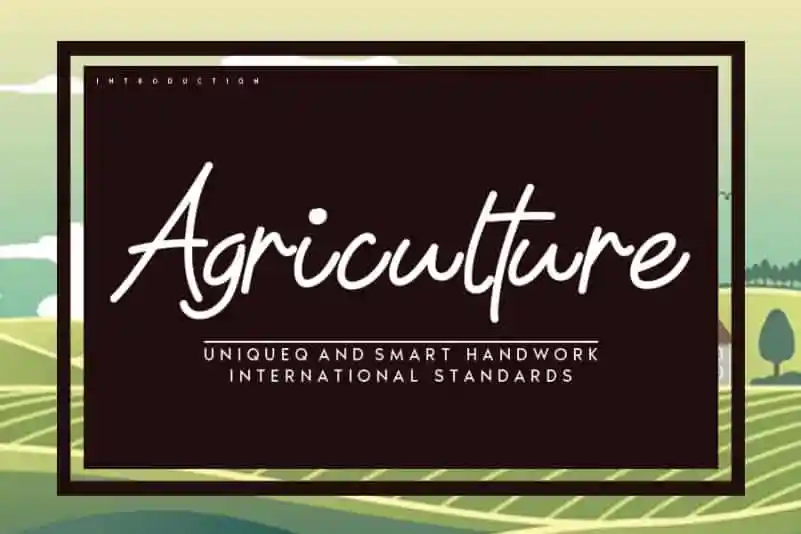
Agriculture Handwritten Font – Download Grátis
Agriculture Handwritten Font é uma elegante escolha para designers que buscam trazer sofisticação à sua próxima obra. Esta fonte escrita a mão se destaca com suas linhas perfeitas e movimentos fluidos, proporcionando um toque refinado a qualquer projeto de design. Seja para marcas, cabeçalhos, designs de casamento, convites, assinaturas, logotipos ou rótulos, ela se destacará. Com sua inspiração clara na arte da calligrafia, esta fonte permite que você traga um toque pessoal e único a seus projetos. Desde as mais sutis detalhes até os elementos mais impressionantes, essa fonte escrita a mão será uma ótima opção para qualquer projeto onde desejará incluir um elemento autêntico e elegante. Para designers que valorizam não apenas criatividade, mas também uma paixão por detalhes finos, Agriculture Handwritten Font é perfeita. Sua estética sofisticada se combina com sua versatilidade para criar uma variedade de opções, tornando-a um recurso indispensável em qualquer projeto que você está desenvolvendo.